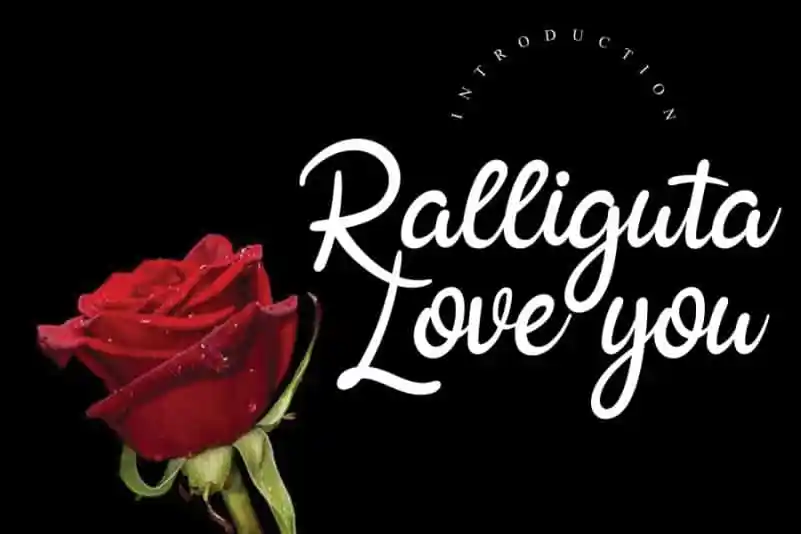
Ralliguta Handwritten Font – Download Grátis
Ralliguta Handwritten Font é uma fonte que oferece a sensação única e encantadora de escrita à mão. Perfeita para aqueles momentos especiais, como festas de casamento ou celebrações de agradecimento, ela também se destaca em cartões de boas-vindas, cartões de felicitação, frases memoráveis e logomarcas. Seja você um designer que busca dar um toque personalizado à sua arte gráfica com uma escrita delicada e autêntica ou alguém buscando a fonte ideal para adicionar um toque especial em seu trabalho de marketing empresarial, esta fonte é uma escolha perfeita. Suas linhas finas e traços leves criam texturas ricas que deixam sua arte imersa em elegância. O designer andikastudio trouxe esta delicada escrita à vida com um toque único que certamente tornará seu trabalho mais atraente e envolvente.